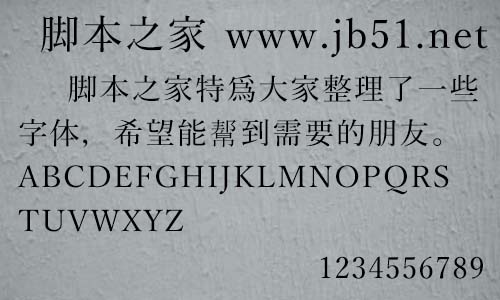
游明朝體yumincho 是一款日系中文字體,這款字體的筆觸較為纖細(xì),字體清晰明朗,端正大氣,適合應(yīng)用于藝術(shù)設(shè)計(jì)、平面宣傳設(shè)計(jì)、網(wǎng)頁(yè)設(shè)計(jì),書法字帖等領(lǐng)域,需要的朋友可以前來(lái)本站下載。